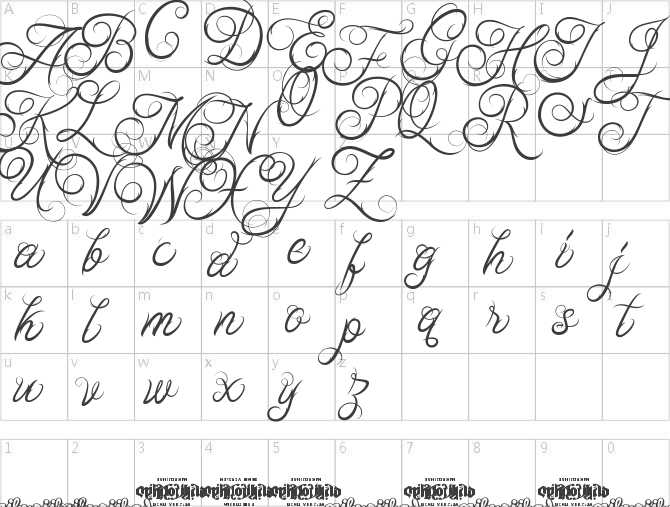
Ababil Script DEMO 详情页
字体名称: Ababil
Ababil Script DEMO
Ababil Script DEMO字体字库是一款让人赏心悦目、百看不厌的英文字体,适合各类广告和产品包装设计应用,字体大小0.72MB,格式为ttf字体,上传用户是随缘゜,作者/版权方为未知